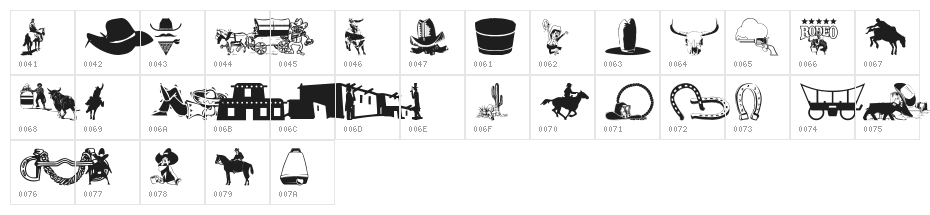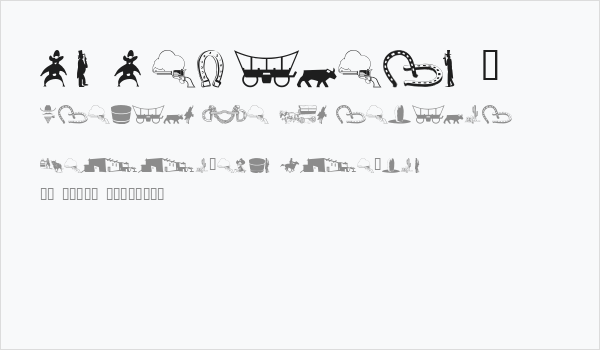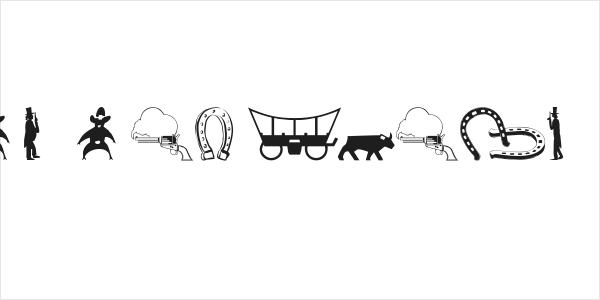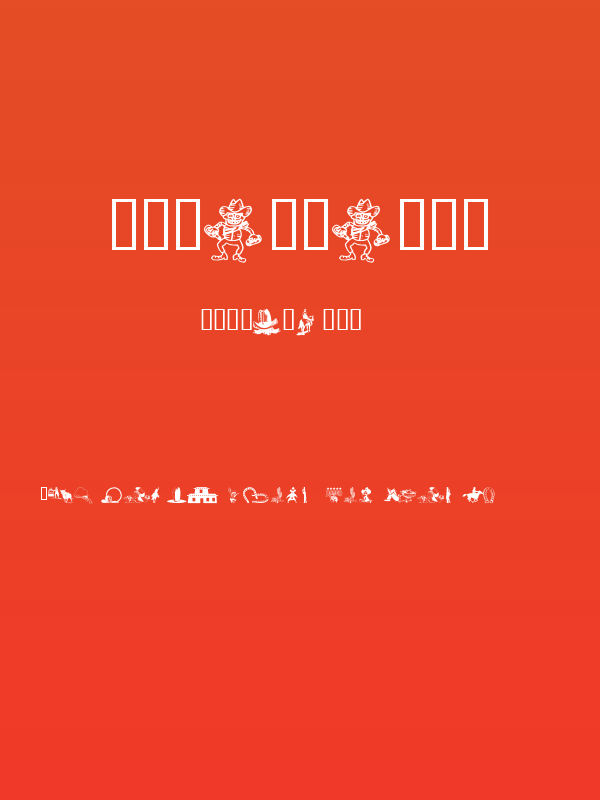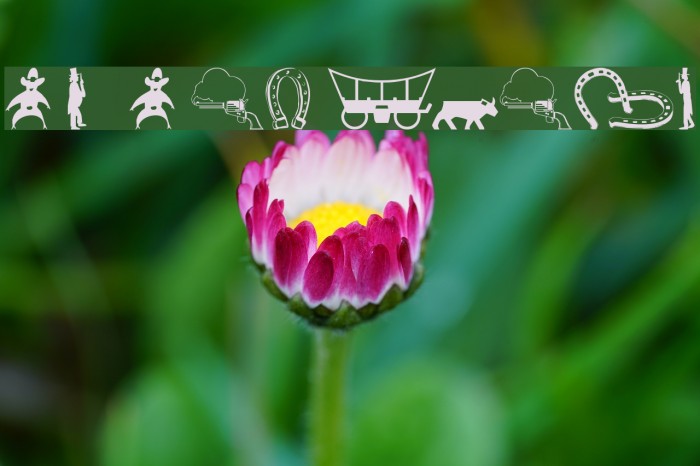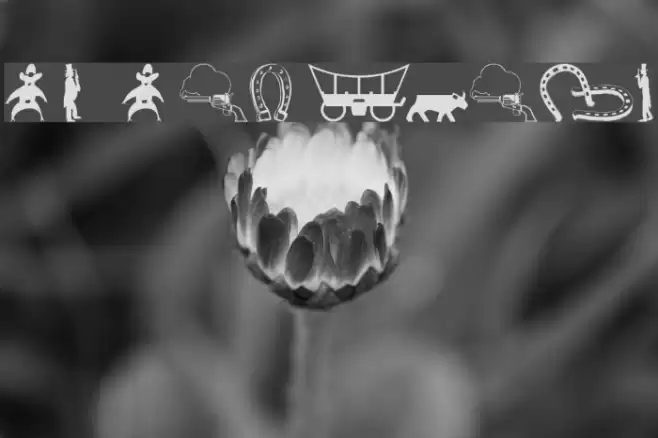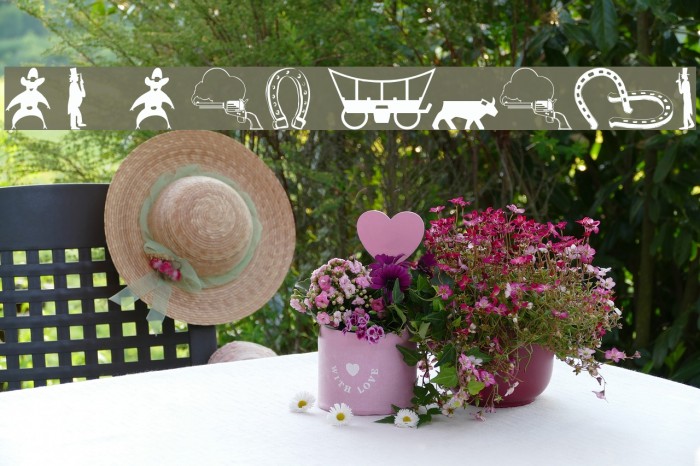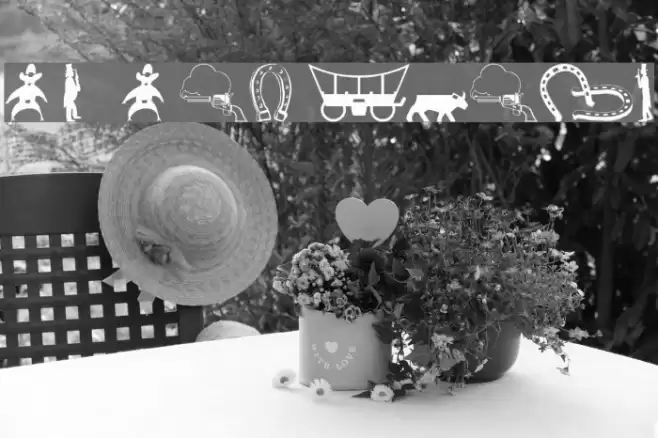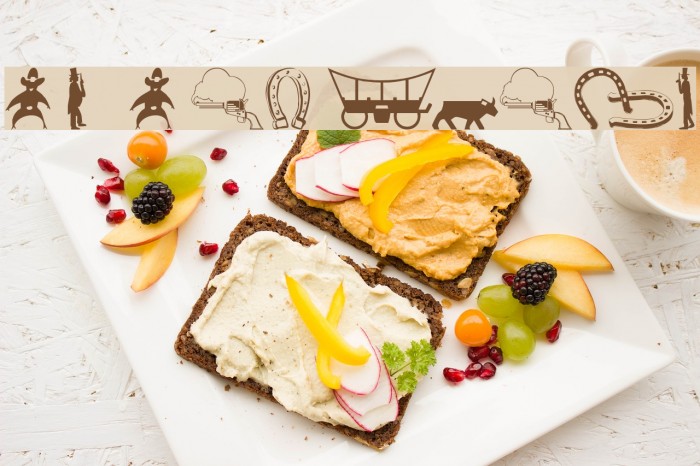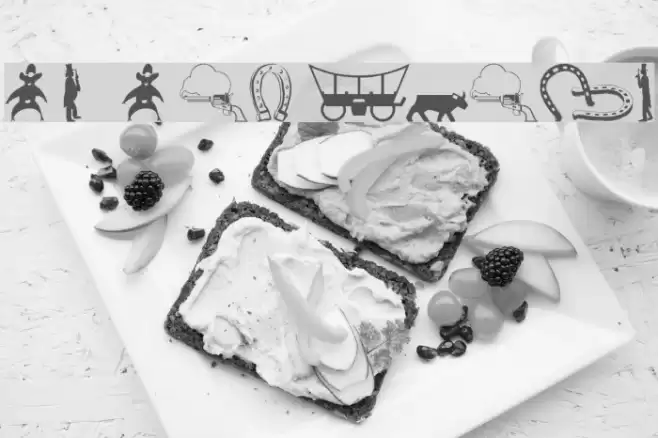
wmwestern1 Font
| 用途 | Logos, Posters, Themed Events |
| おすすめプロジェクト | Ideal for themed event invitations, posters, or educational materials about the Wild West. |